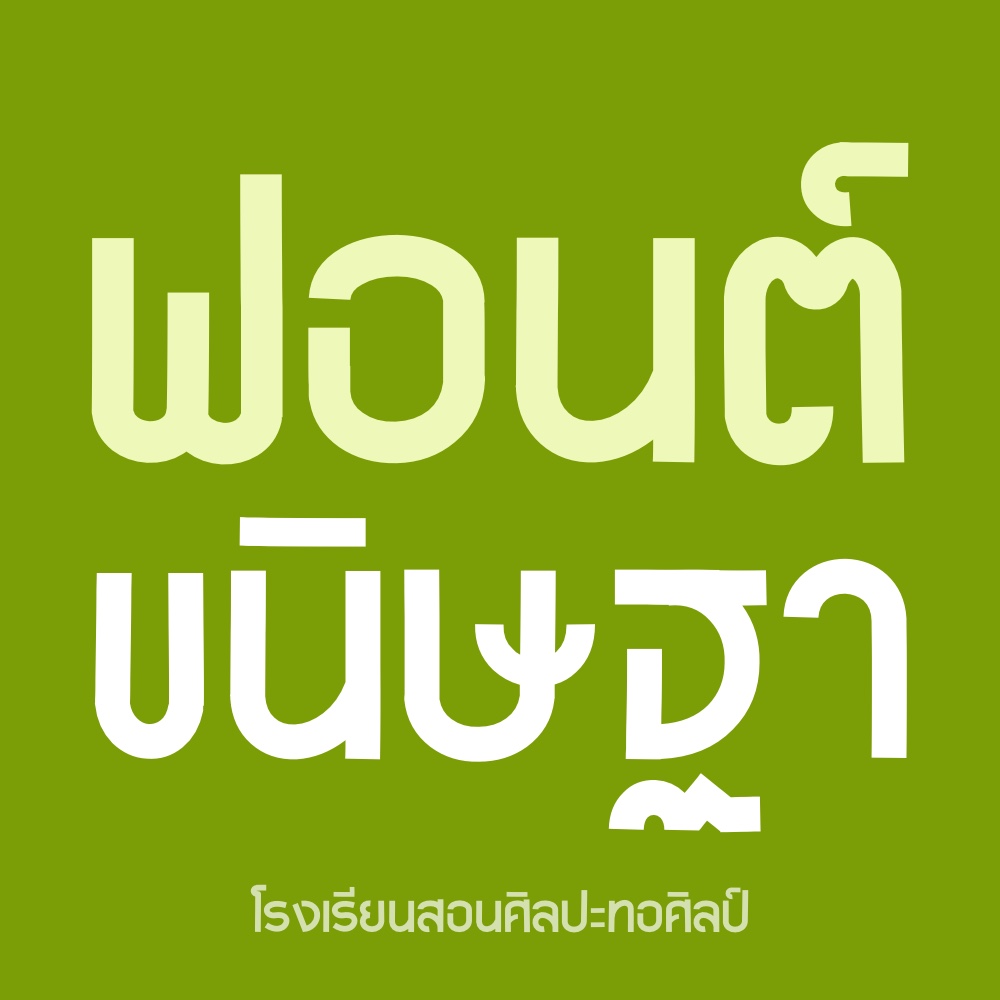
ทอศิลป์ขนิษฐา
ทำฟอนต์ตัวยากๆ สำเร็จอีก
ตัวนึงแล้ว ภูมิใจมากครับ
ฟอนต์ยากตัวแรกคือฟอนต์ตัว
พื้นที่อ่านง่าย "ทอศิลป์เรียงความ"
อันนั้นทำสำเร็จไปแล้ว
มีฟอนต์อีกรูปแบบนึง
ที่ทำยากเหมือนกันคือฟอนต์
ไม่มีหัวเพื่อใช้เป็นดิสเพลย์
พวกหัวข้อเน้นๆ ใหญ่ๆ นี่แหละครับ
ชื่อฟอนต์ "ทอศิลป์ขนิษฐา"
ฟอนต์โดย
ระจัน โรงเรียนสอนศิลปะทอศิลป์